今回は、雪朱里 著の「『書体』が生まれる」を紹介します。
刊行記念のオンライントークイベントでは、著者の対談相手をタイププロジェクト代表・タイプディレクターの鈴木功が務めました。
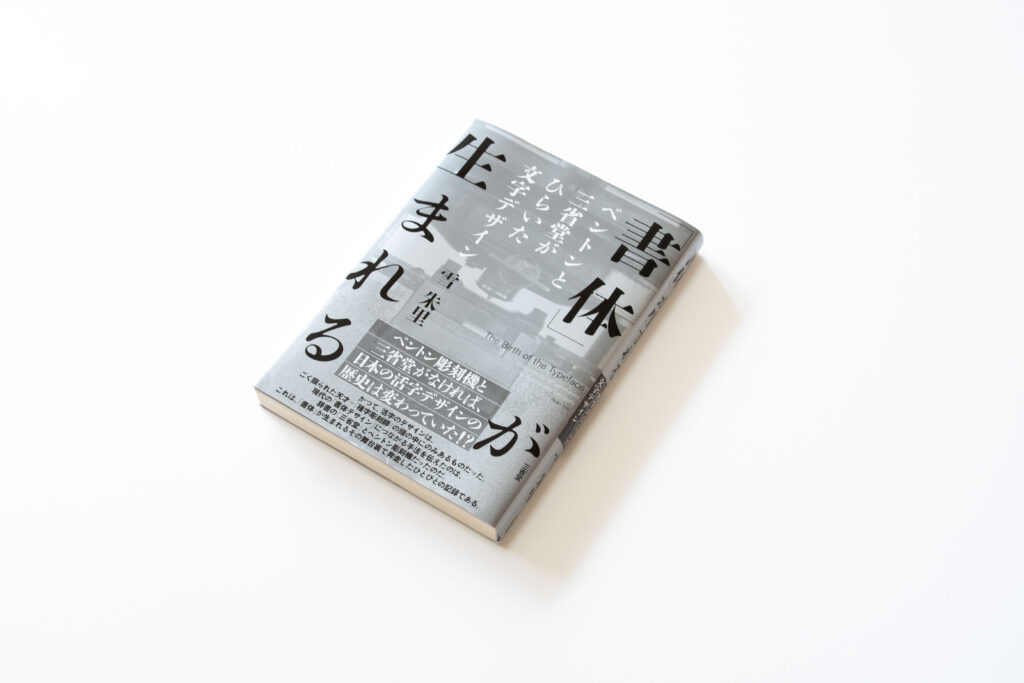
本書では、金属活字における書体デザインを大きく変えた「ベントン彫刻機」と、日本における導入のきっかけとなった「三省堂」について、その歴史が描かれています。
かつて、金属活字は種字彫刻師によって彫られて制作されており、その技術は非常に高度なもので、種字彫刻師も限られた存在でした。
ベントン彫刻機では、紙にレタリングした原図から機械的に彫ることができるようになったため、活字制作の効率化や印刷品質の向上だけでなく、種字彫刻師のみによって生み出されていた活字のデザインも開かれたものになりました。
文字のアウトラインを描いてそれを活字(フォント)にするという、現代でも一般的な書体デザインの手法、ベントン彫刻機はその原点と言えます。
一方、三省堂の創業者である亀井忠一は「よいものは必ず、美しい」という信念のもと、自社の印刷工場を作るほどに印刷の美しさを大事にしていました。
創業者の四男・亀井寅雄は、それでもなお当時の水準に満足できず、さらなる印刷品質を追求した結果、たどり着いたのがベントン彫刻機でした。
この運命的な交差から、亀井寅雄による大変な苦労の末、三省堂にベントン彫刻機が導入され、これをきっかけとして日本国内にベントン彫刻機が流通します。本書では、この様子が膨大な資料とインタビューを通して深く記述されています。
トークイベント内では、Bézier(ベジェ)曲線に関するトピックも出てきました。これによって、物理的制約のないきれいな曲線を描くことができるようになりました。しかし、その数学的な性質により、実際の操作には一定の慣れが必要です。Bézier曲線より自然にきれいに描けるような方法があれば、さらなる書体デザインの進化の可能性があるのではないかと、ベントン彫刻機のエピソードと重ねて思うところがありました。
ちなみに、タイププロジェクトは練馬区の石神井にありますが、本書によると、戦時中のベントン彫刻機の疎開先のひとつに石神井の神学校があったそうで、石神井と書体の意外な関わりを知りました。
ベントンで彫刻した母型に種字彫刻師が手を入れて直したという記述や、ベントン彫刻機の扱いに腐心した様子、ベントン彫刻機を導入した各社で書体研究が行われ一から書体デザインを模索していった経緯などから、機械が万能で精巧であってもそれを扱う人間の目や技術を合わせて良いものにしていくことはデジタルフォントの制作でも変わらないと感じました。
ベントン彫刻機以降の道具の特性や制約による鮮明な文字と、全て人の手で彫られた文字と比べたときの精密さによっては生まれない線についての違いは、現在のフォント制作をする中のみでは気づけない点でした。
日本の「書体デザイン」の源流にあたる重要な人物や歴史を知る手引きとしてもおすすめの一冊です。
『「書体」が生まれる ベントンと三省堂がひらいた文字デザイン』